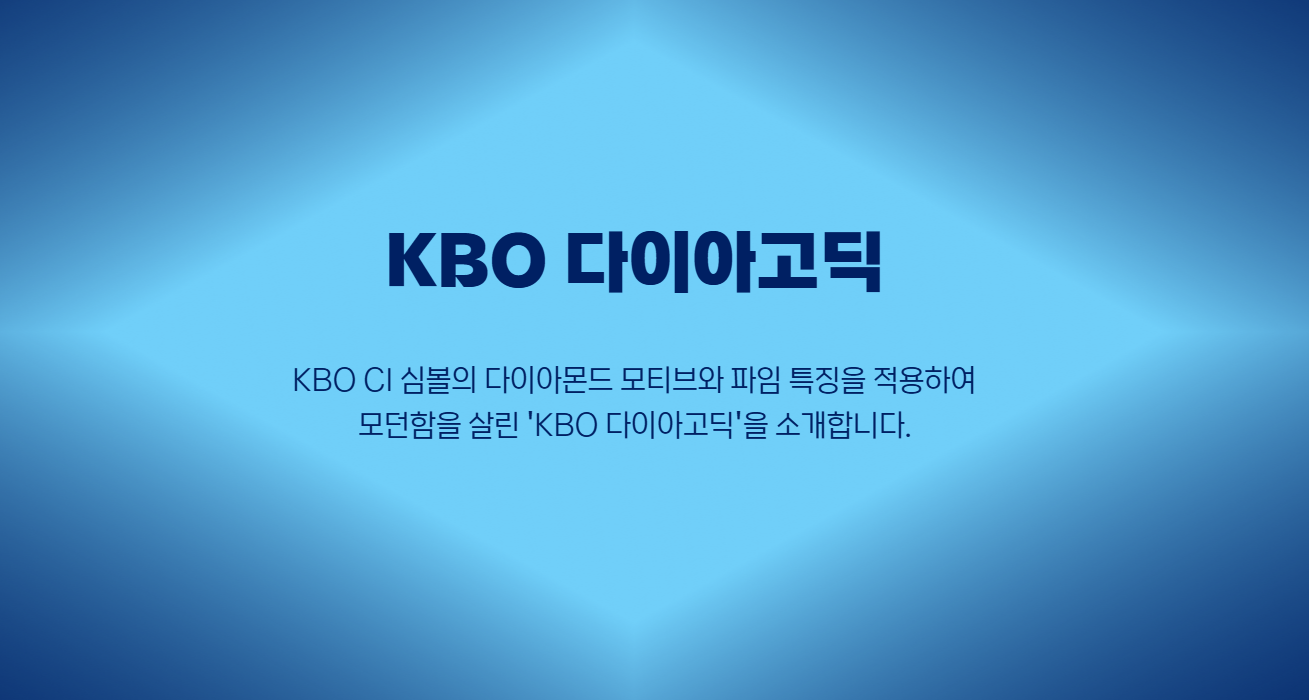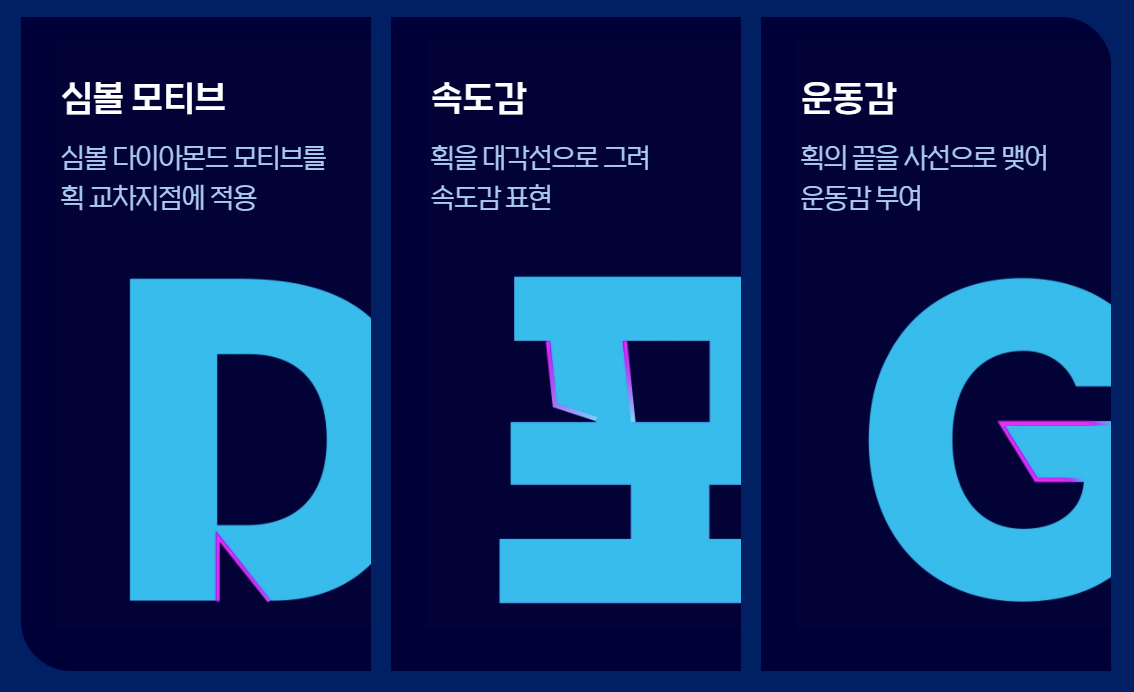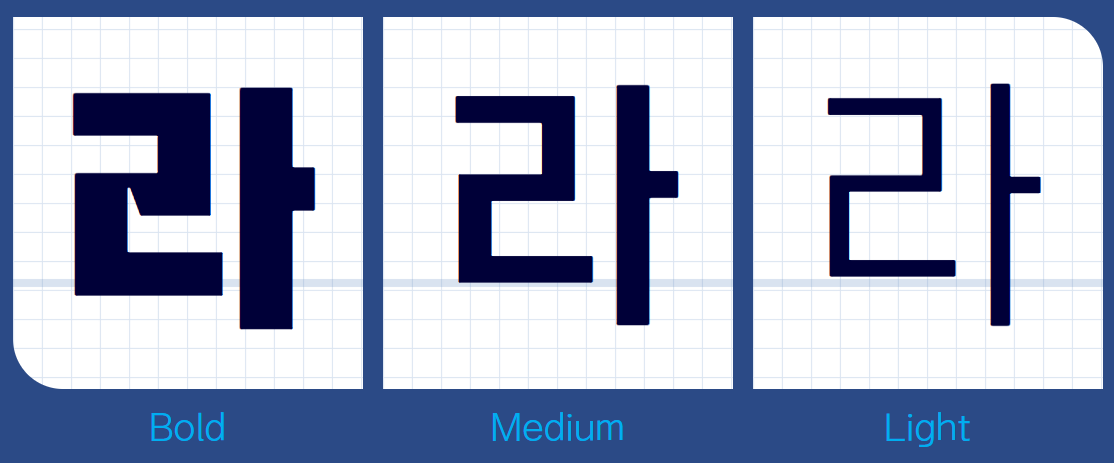
최근 한국 프로야구(KBO)가 사상 최초로 1,000만 관중 시대를 열며 엄청난 인기를 누리고 있습니다. 야구장의 뜨거운 함성만큼이나 블로그, 유튜브, SNS 등에서 야구 관련 콘텐츠를 만드시는 분들도 정말 많아졌는데요.
야구 관련 디자인을 할 때, 항상 고민되는 것이 바로 '어떤 폰트(글꼴)를 쓸까?'입니다. 밋밋한 고딕체보다는 야구의 역동성을 담은 서체가 필요하지 않으신가요? 오늘은 KBO의 아이덴티티를 완벽하게 담아낸 공식 'KBO 폰트'의 탄생 배경부터 다운로드, 그리고 가장 중요한 저작권 정보까지 꼼꼼하게 정리해 드립니다.
KBO 폰트, 어떤 서체인가요? (제작 배경 및 특징)
KBO 폰트는 한국야구위원회(KBO)가 리그의 브랜드 아이덴티티(BI)를 통합하고 강화하기 위해 개발한 전용 서체입니다.
- 제작 배경: 과거 KBO 리그는 통합된 비주얼 아이덴티티가 부족하다는 평이 있었습니다. 이에 KBO는 리그의 브랜드 가치를 높이고 팬들에게 통일된 시각적 경험을 제공하기 위해 새로운 엠블럼과 함께 전용 서체를 개발하여 배포하게 되었습니다.
- 디자인 특징:
- 강인함과 역동성: 투수가 공을 던지거나 타자가 배트를 휘두르는 순간의 에너지를 서체의 획에 담았습니다.
- 직선과 곡선의 조화: 단단한 직선은 승부의 공정함을, 유려한 곡선은 경기의 흐름을 상징합니다.
- 가독성: 전광판이나 자막 등 다양한 환경에서도 잘 보이도록 굵고 시원시원하게 디자인되었습니다.
KBO 다이아고딕은 Bold, Medium, Light로 같은 뼈대로 제작하여 시각적 통일성과 가독성을 모두 살린 3종의 서체로 구성되어 있습니다.
활용 예시: 이렇게 써보세요!
KBO 폰트는 굵기가 굵고 임팩트가 강해 '제목용 서체'로 아주 적합합니다.
- 유튜브 썸네일: "오늘의 하이라이트", "역전 만루 홈런!" 등 강조하고 싶은 문구에 사용해 보세요.
- 블로그 헤더: 야구 관람 후기 포스팅의 제목을 KBO 폰트로 꾸며보세요.
- 응원 피켓: 야구장에 갈 때, 좋아하는 선수의 이름을 KBO 폰트로 출력해 응원 도구를 만들어보세요.